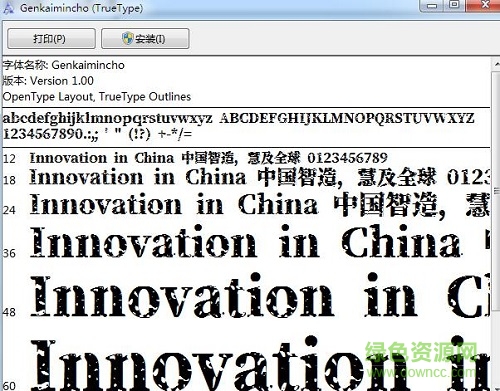
源界明朝體是一款充滿著藝術(shù)氣息的電腦字體,根據(jù)著名的思源字體改編而來,加入了視覺上的破碎效果,使得整個界面看起來非常的獨特,有需要的朋友歡迎下載!
這款字體是以思源宋體為基礎(chǔ),加入破壞效果使其最接近可讀狀態(tài),可以簡單理解成思源宋體的破壞版,源界明朝在視覺上具有相當(dāng)大的張力,可作為圖片內(nèi)的標(biāo)題和大字使用,整體來說相當(dāng)吸睛且頗具效果。